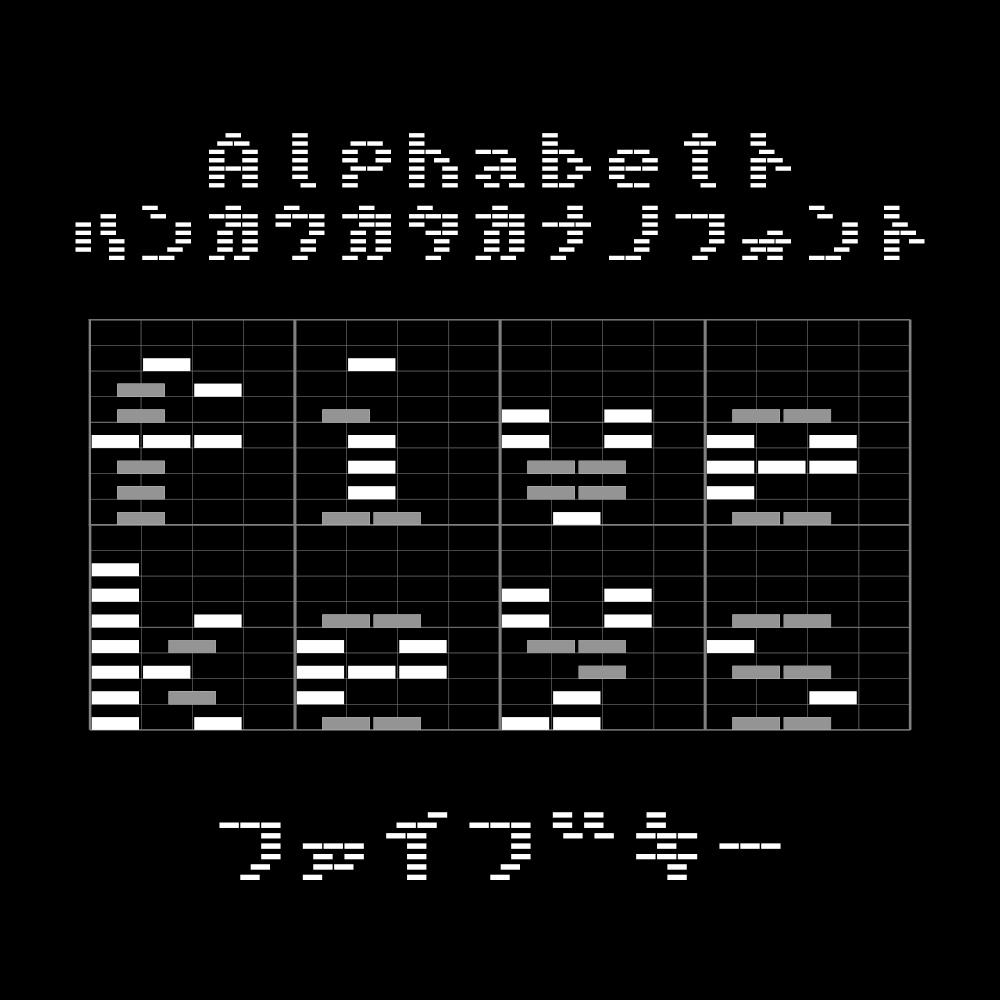
torisippoフォント five keys ファイブキーDigital0 JPY免费下载fivekeys_v1.0.zip (36.2 KB)fivekeys_v1.0.zipAbout Gift変則的なドットフォントです。フォントデータ形式TrueType(.ttf)更新履歴2026/08/06 v1.0 新規作成 torisippoVisit FANBOX!Fontsフォント Auxiliary line オーグジュアリラインtorisippo0 JPYFontsフォント でんでんえん/でんえんえんtorisippo1,200 JPYFontsフォント DOThoundstooth ドットハウンドトゥース(ドット千鳥格子)torisippo0 JPYFontsフォント ひらすわぷろtorisippo800 JPYFontsフォント PCB10 プリント基板配線パターンフォントtorisippo0 JPYFontsフォント MahjongMPSZColortorisippo0 JPYFontsフォント DOTjigsaw (fontforge用フォント生成スプリクト付き)torisippo0 JPYSoftwareFormat Renamer ~キーボードを極力使わないリネームソフト~torisippo1,000 JPYFontsフォント マステ丸 ラウンド25torisippo0 JPYFontsフォント ひらすわtorisippo0 JPYFontsフォント メニーワンtorisippo0 JPYFontsフォント MahjongZSPMtorisippo0 JPYFontsフォント MahjongMPSZtorisippo0 JPYFontsフォント ブルーテイルtorisippo0 JPYFontsフォント デンエンtorisippo0 JPYFontsフォント カールtorisippo0 JPYFontsフォント ウォータービーズtorisippo0 JPYFontsフォント ウーファーtorisippo0 JPYFontsフォント ラバーボールtorisippo0 JPYFontsフォント フォースフルドットtorisippo0 JPY查看更多